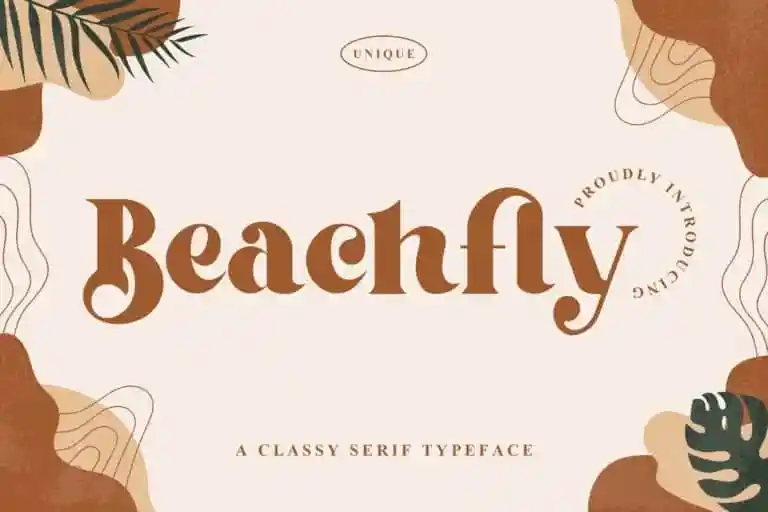
Beachfly Serif Font – Download Grátis
A Beachfly Serif Font é uma tipografia de serif que foi criada pela typefactory para aqueles amantes do design retro. Com seu estilo distintivo e sofisticado, esta fonte combina um toque de elegância e delicadeza clássica com elementos vintage. Perfeita tanto para projetos tradicionais quanto para inovações modernas, ela se destaca em qualquer projeto. Suave e confortável para leitura em grandes tamanhos, Beachfly é uma ótima escolha para invitations de casamento, postagens chamativas nas redes sociais, cartões de agradecimento criativos e mais. Não há dúvidas de que esta fonte trará vida e energia aos seus projetos visuais.